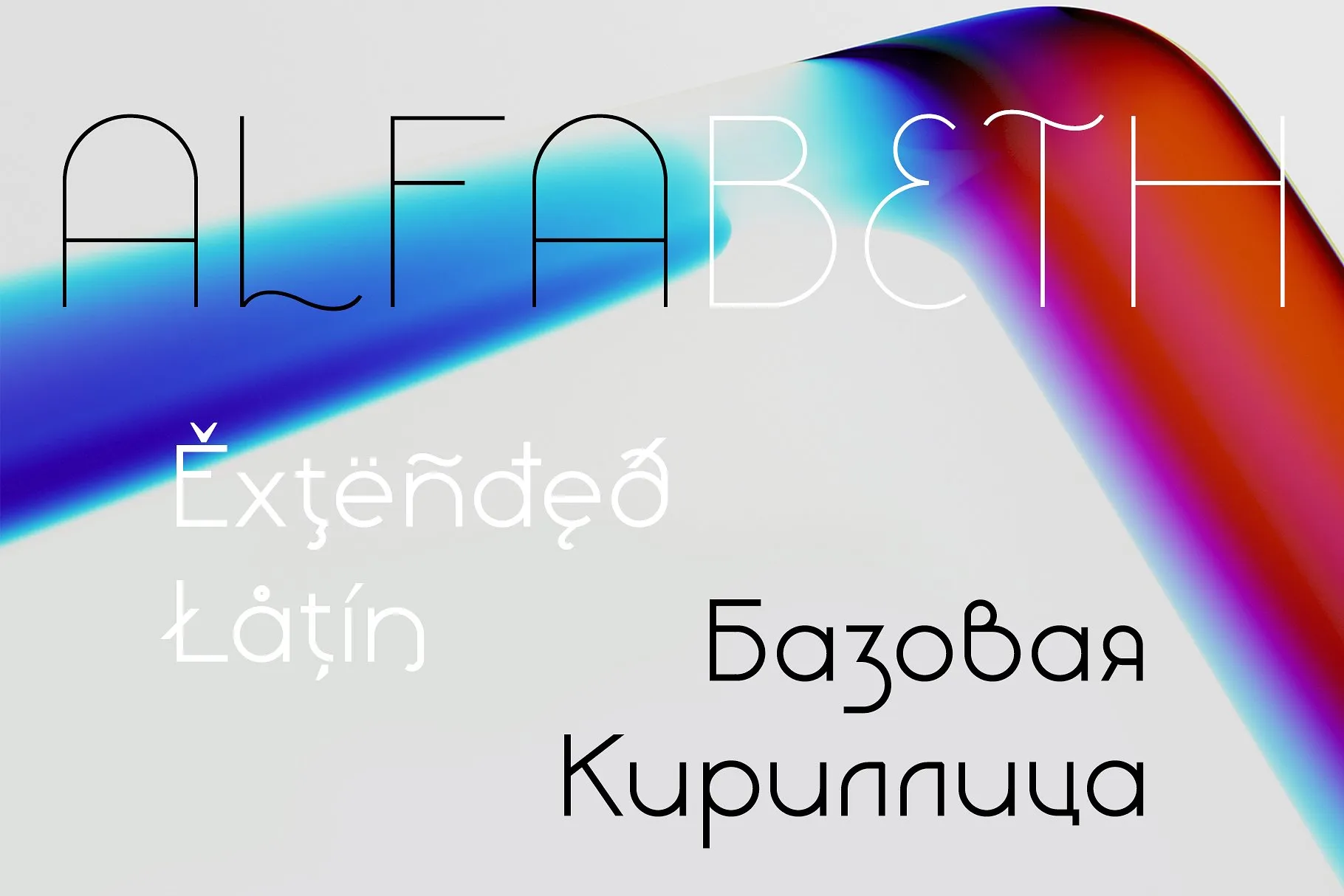
Кириллический шрифт Liberal family
Получите доступ к гарнитуре Liberal family — шрифтовому семейству 2018 года с поддержкой кириллицы. В набор входят начертания, подходящие для оформления заголовков и текстовых блоков, где требуется выразительная типографика. Материал включает файлы шрифтов, готовые к установке и использованию в графических редакторах и верстке.